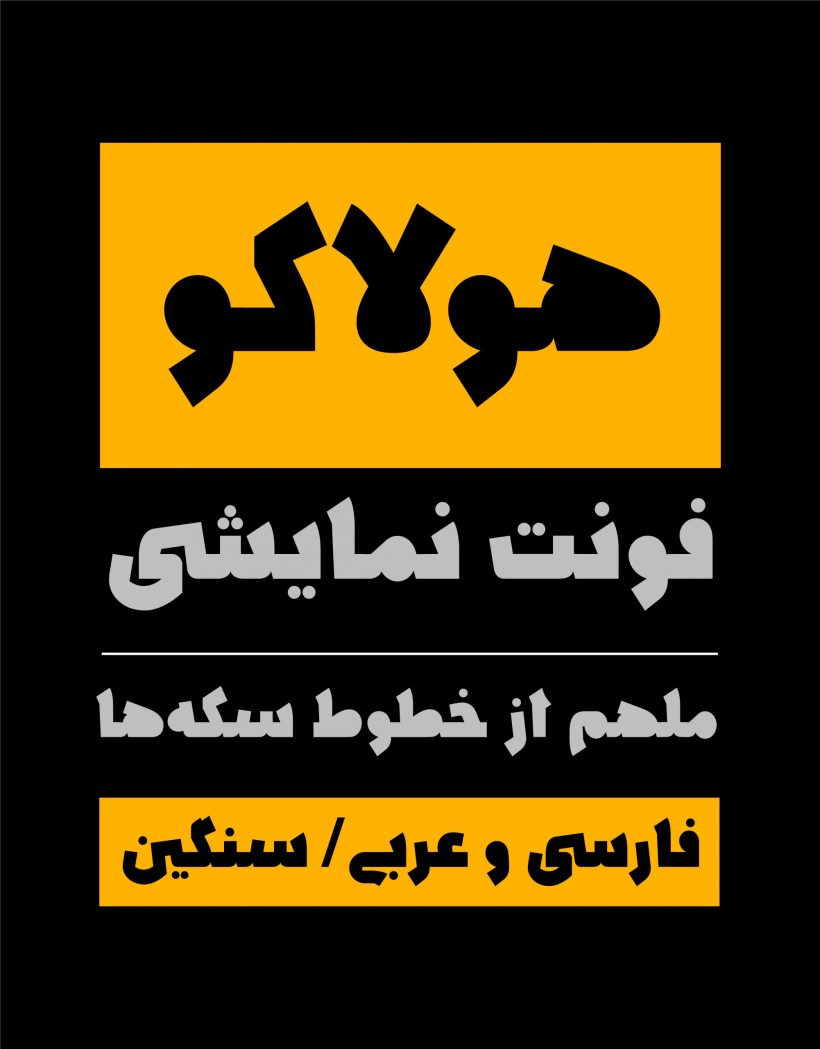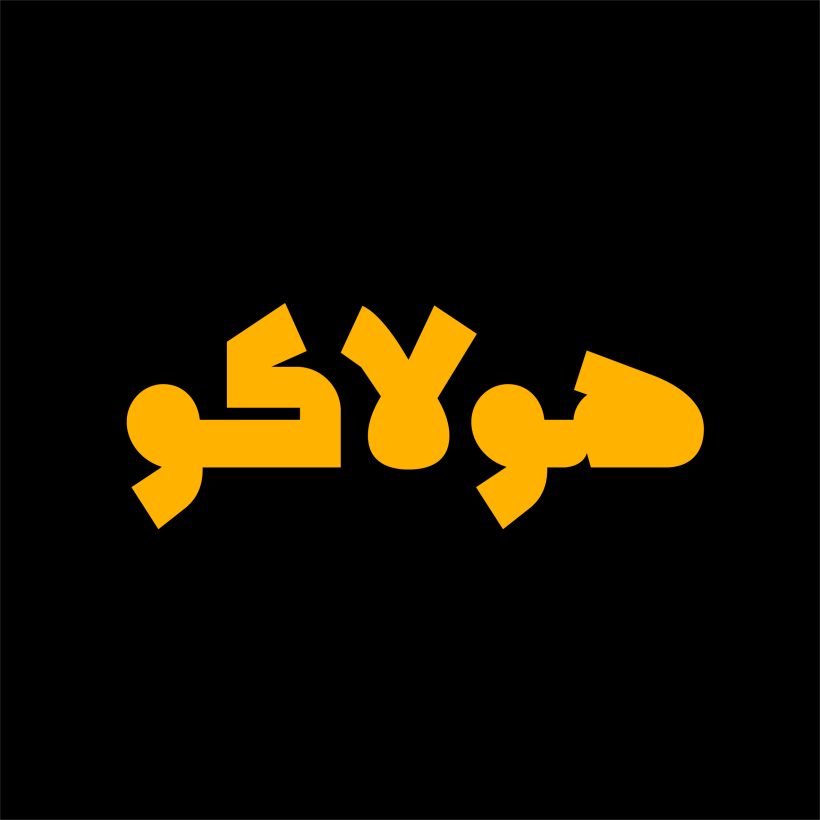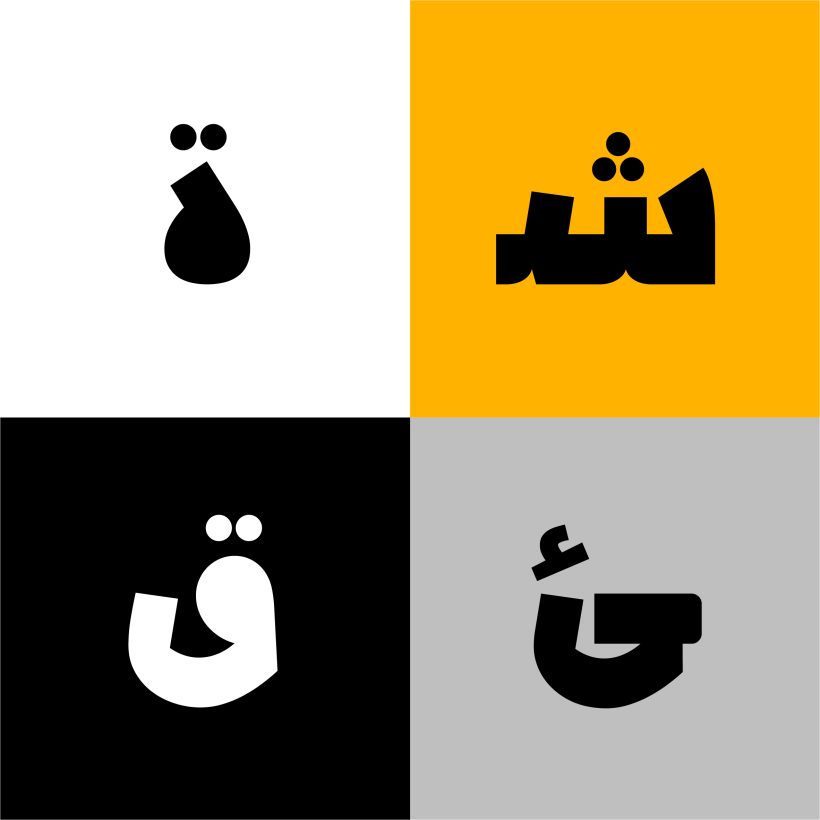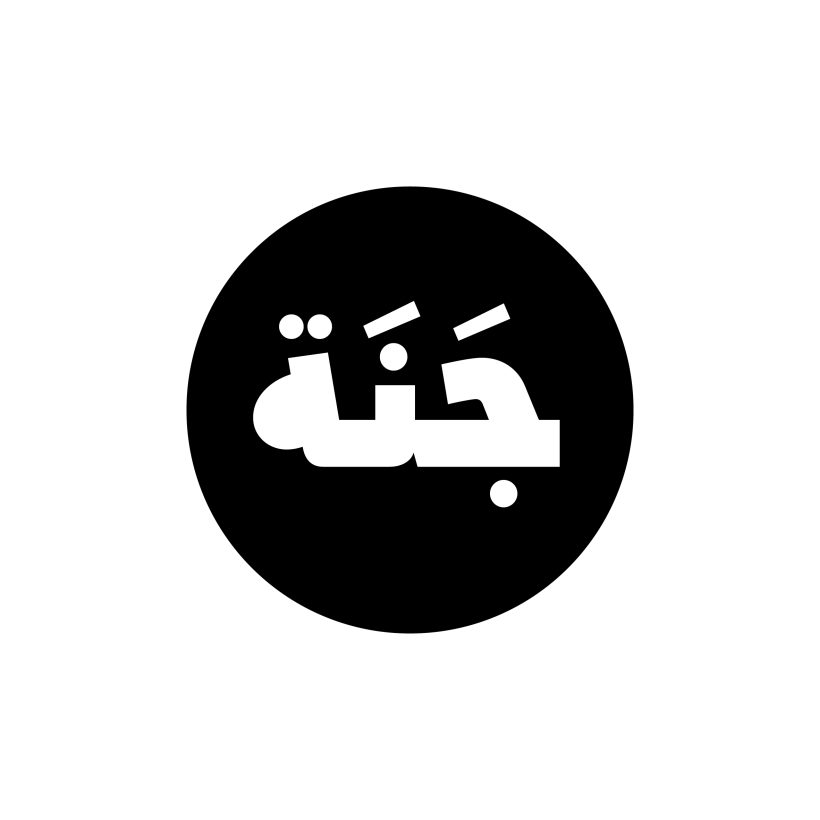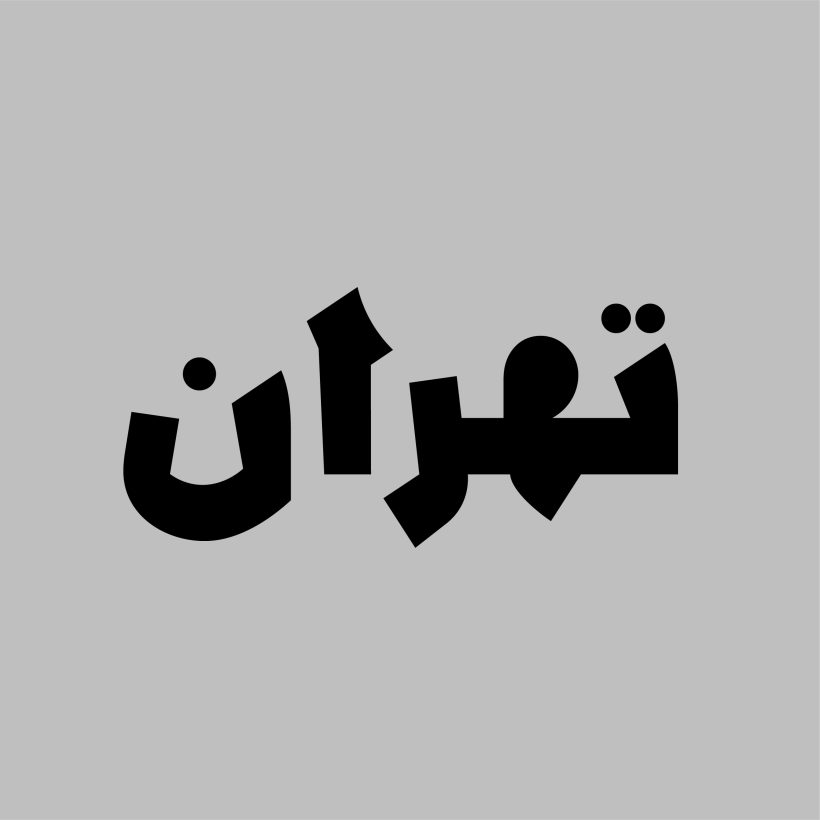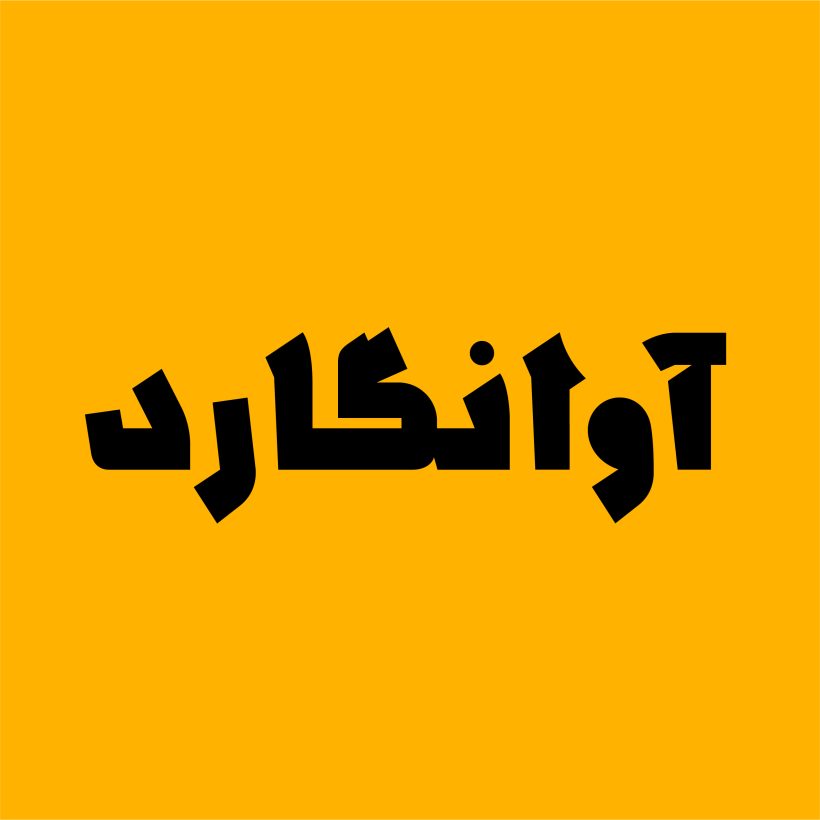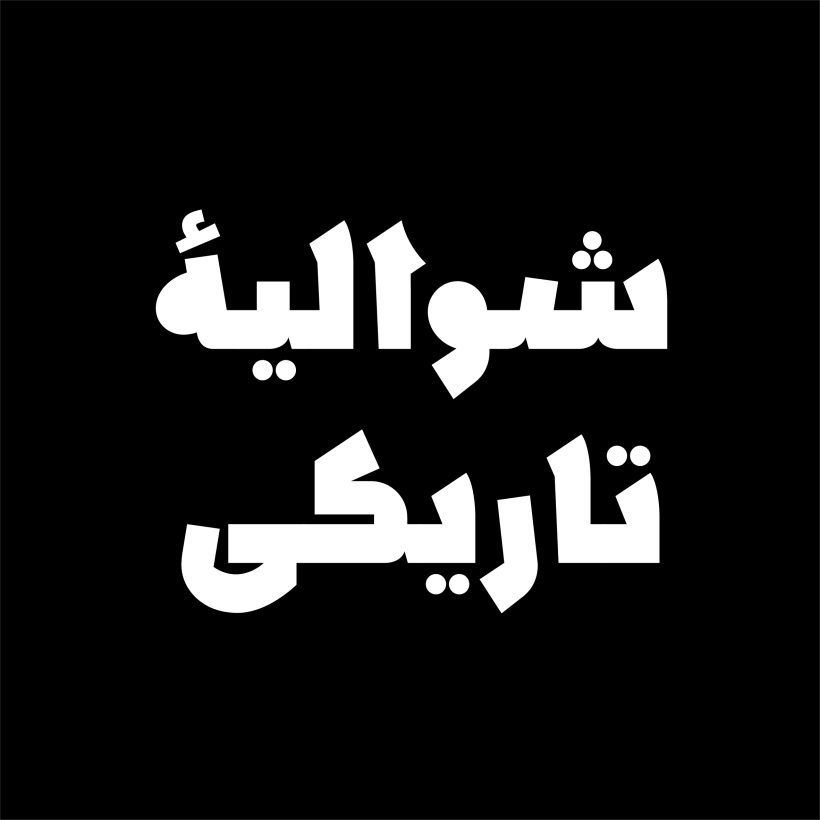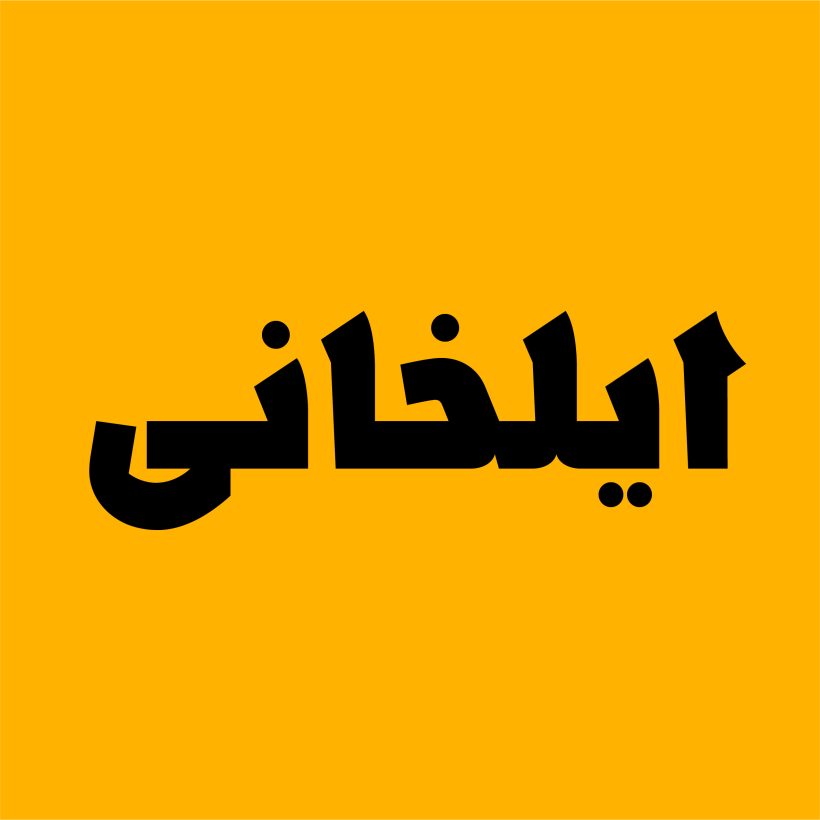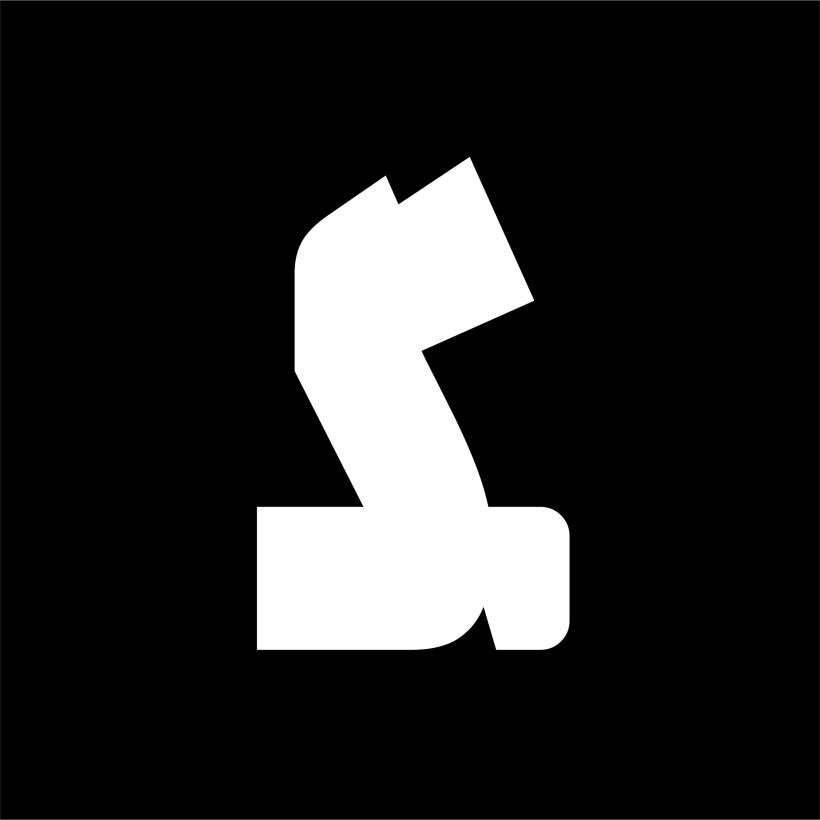
فونت هولاکو
فونت هولاکو با الهام از خط کوفی سکه نقره مونگکا قاآن [خان بزرگ مغول]؛ محفوظ در کتابخانه و موزه ملی ملک طراحی شده است. معمولا نام هولاکوخان بر روی سکه‌های دوره ایلخانی، در کنار نام خان بزرگ مغول می‌آمد و علت نامگذاری این نام نیز همین است.
هولاکو فونت نمایشی، متمایز، سنگین و توپر است که در یک وزن طراحی و اجرا شده است. در این فونت حروف از نظر فرم به گونه‌ای طراحی شده‌اند که نسبت سطح بیشتری دارند و چشم‌ها و فضاهای منفی برای تاکید بیشتر توپر در نظر گرفته شده‌اند. به دلیل کنتراست ضخامتی زیاد و اغراق‌هایی که در فرم حروف ایجاد شده است؛ بهتر است که از آن در عناوین و جملات کوتاه استفاده شود.
در فونت هولاکو قواعد کرنینگ و اعراب‌گذاری به طور کامل رعایت شده است. همچنین هولاکو دارای لیگیچر و کاراکترهای جایگزین می‌باشد و این امکان را به مخاطب می‌دهد تا متناسب با نیازش، گزینه و فرم مناسب را انتخاب نماید.
طراح فونت: شکوفه علویان